Pulau Halloween
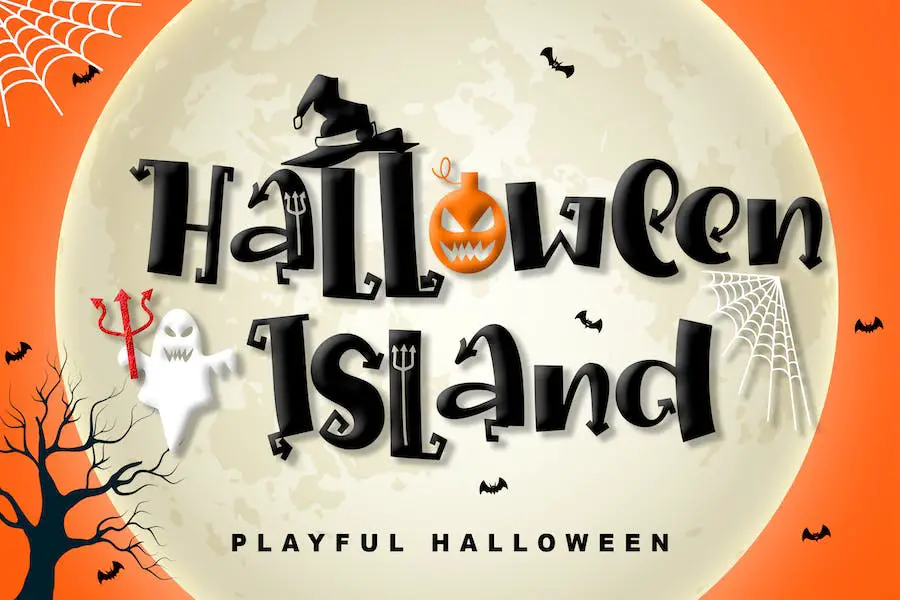
Pulau Halloween adalah font luar biasa yang menambahkan sentuhan unik dan berani pada desain Anda. Dengan tulisan dekoratif dan ekstra kerennya, font ini sangat cocok untuk semua proyek bertema Halloween Anda.
Rahasia Halloween
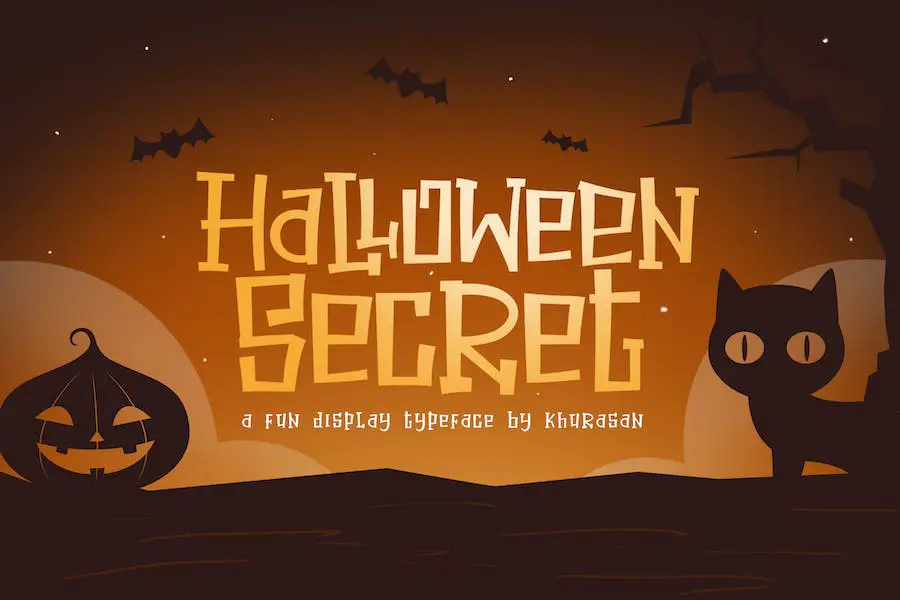
Rahasia Halloween adalah font tampilan fantastis dengan tema Halloween seram yang akan meningkatkan proyek Anda ke tingkat yang baru. Baik itu logo, branding, kartu ucapan, poster, atau desain apa pun yang dapat Anda pikirkan, font ini sangat cocok.
Estetikanya yang menakutkan akan menambah lapisan kesenangan dan kreativitas ekstra pada karya Anda, membuatnya menonjol dari keramaian. Dengan Halloween Secret, Anda akan dapat menciptakan suasana Halloween yang sempurna dan memberikan proyek Anda sentuhan seram yang mereka butuhkan.
Jadi, bersiaplah untuk terjun ke dunia font Halloween dan biarkan kreativitas Anda menjadi liar.
Beyone
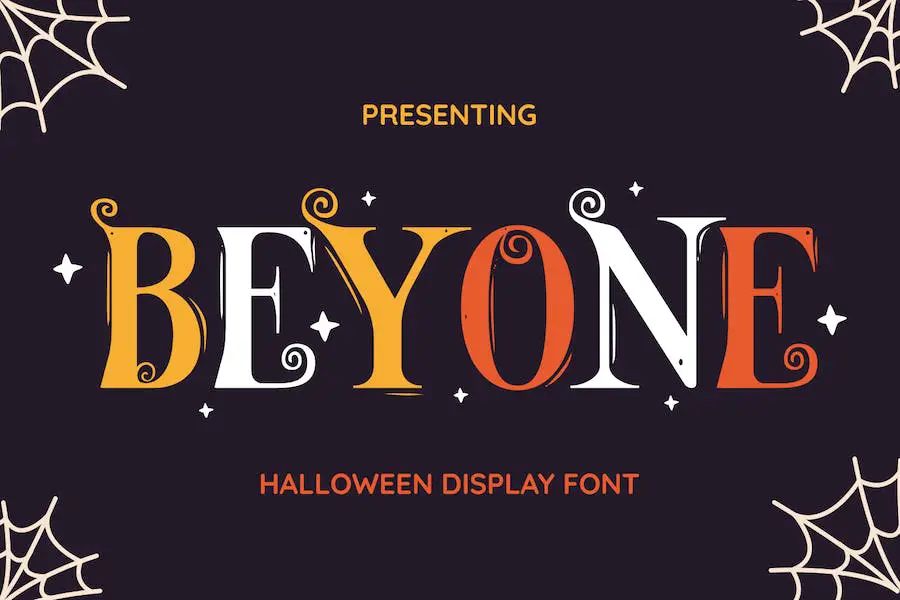
Beyone adalah font Halloween seram yang sempurna untuk menambahkan sentuhan ketakutan pada proyek desain Anda.
Apakah Anda sedang membuat logo seram, materi branding, sampul buku, atau bahkan kaos bertema Halloween, font ini pasti akan membuat pernyataan. Dengan gayanya yang unik dan menakutkan, pasti akan menarik perhatian.
Salah satu hal hebat tentang Beyone adalah keserbagunaannya. Ini tidak terbatas hanya pada proyek bertema Halloween; itu juga dapat digunakan untuk majalah, berita utama, dan lainnya.
Font dilengkapi dengan huruf besar dan kecil, serta angka dan tanda baca. Ini berarti Anda memiliki semua yang Anda butuhkan untuk membuat desain yang menakjubkan.
Yang membedakan Beyone adalah dukungan multibahasa dan fitur Opentype-nya. Jadi, apa pun bahasa yang Anda gunakan, font ini membantu Anda. Anda dapat mencampur dan mencocokkannya dengan font lain untuk membuat desain yang lebih menakjubkan.
Noganas
Noganas adalah font Halloween seram yang disebut 'The It Halloween Typeface'. Ini dirancang khusus untuk konsep dan acara desain bertema Halloween di bulan Oktober dan November.
Dengan karakter horor dan bentuknya yang terdistorsi, font ini menambahkan sentuhan unik dan menakutkan pada setiap desain Halloween.
Tapi itu belum semuanya! It Halloween Typeface juga hadir dengan bonus 150 ilustrasi bertema Halloween. Hal ini membuat pembuatan desain Halloween menjadi lebih mudah dan menyenangkan. Dengan hanya mengunduh font ini, Anda dapat dengan cepat dan mudah membuat desain seram Anda sendiri.
Noganas tidak hanya sempurna untuk brosur, desain sampul majalah, dan selebaran, tetapi juga bagus untuk iklan Instagram dan desain Canva. Konsepnya yang gelap dan terinspirasi Halloween menjadikannya pilihan serbaguna untuk berbagai proyek.
Pesta Halloween
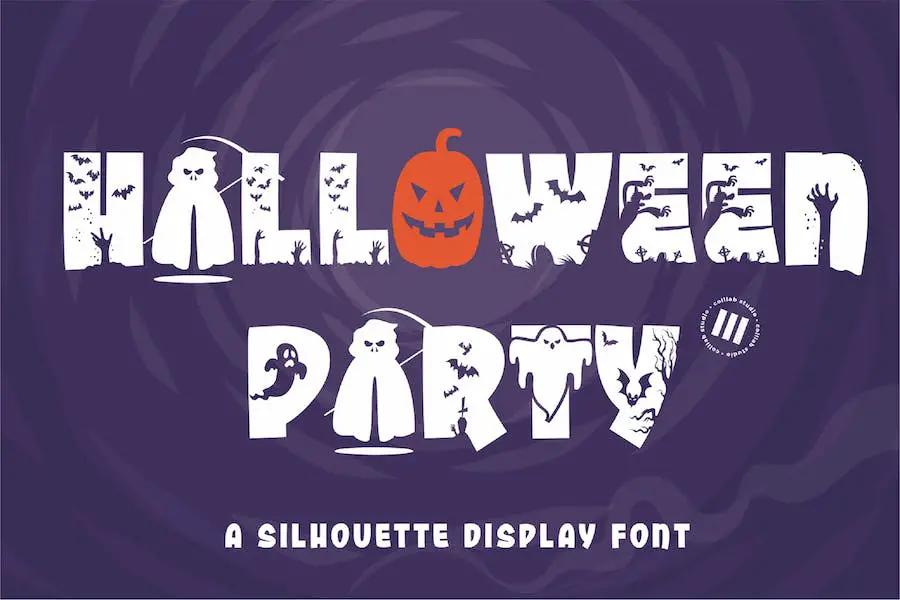
Pesta Halloween adalah font tampilan siluet dengan karakter dekoratif, cocok untuk menambahkan sentuhan seram dan menakutkan pada desain Halloween Anda. Font ini memiliki gaya trendi dan feminin, menjadikannya unik dan menarik.